美しい日本のくせ字
株式会社パイ インターナショナル発行による井原奈津子氏著書の、文字から時代を探る新感覚の書籍「美しい日本のくせ字」が2017年5月22日に発売されている。
「美しい日本のくせ字」は、くせ字蒐集家の井原奈津子氏が約30年に渡って採取したくせ字コレクションには、稲川淳二や南伸坊、また世界的スターであるレディ・ガガ、王羲之などの古典文字、その他にも道ばたで拾ってきた名もなき文字までを紹介。
井原氏は様々なくせ字を通して何を読み解くのか、深くてちょっと曲がったくせ字の世界を満喫できる一冊。
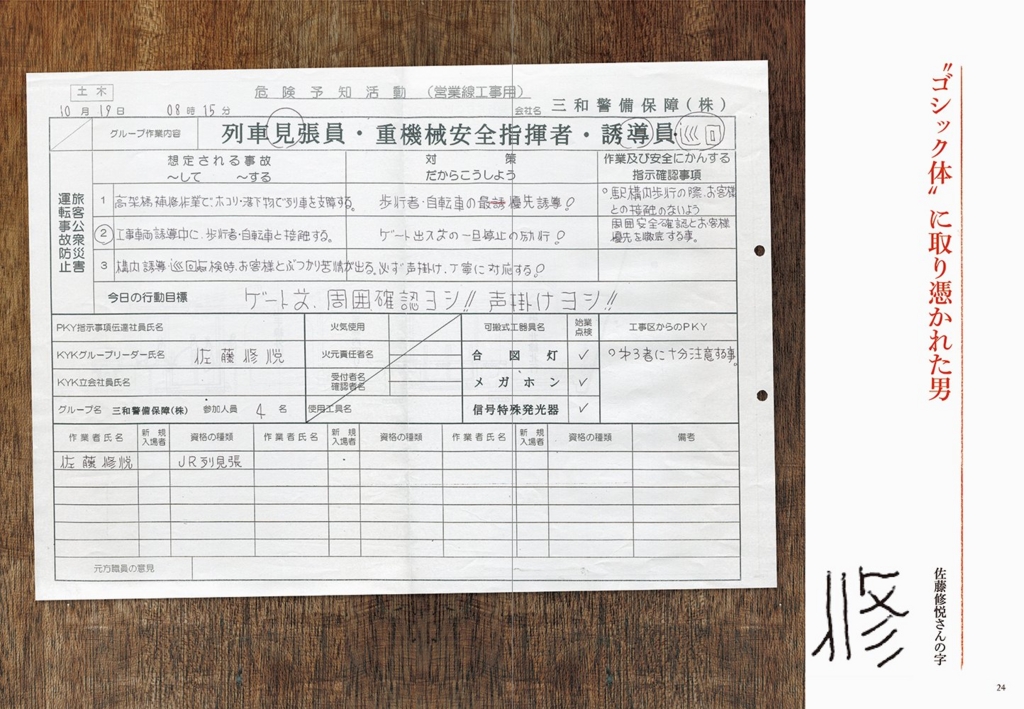
井原奈津子氏
くせ字愛好家。多摩美術大学卒業後、主にエディトリアルデザインに関わる。現在は筆耕、習字の指導などを行い、「くせ字練習会」などのワークショップも開催している。
マツコの知らない世界で取り上げられた「くせ字の世界」
2017年10月17日の「マツコの知らない世界」には井原奈津子氏自身が出演し「くせ字の世界」として取り上げられた。
くせ字蒐集家の井原奈津子は2017年10月17日のマツコ・デラックスの冠番組であり、TBS系列で放送されているトークバラエティ番組「マツコの知らない世界」に出演し、「くせ字の世界」を紹介された。
番組内で中森明菜や小沢健二などの書くくせ字が好みと語っていた。ただのファンにも思えてもくる内容でマツコにもあまりハマっていなかったようだが…。
私の愛するお気に入りのくせ字たちでは、くせ字を愛するきっかけとなった予備校講師の字、ガムテープを使用した案内表示文字の書体「修悦体」で知られる佐藤修悦さん、ミュージシャンの小沢健二などの文字を紹介。
修悦体
主にガムテープとカッターナイフを使用した直線とアールによって描かれた文字。2008年の映画『まぼろしの邪馬台国』の題字にも使用されている。
井原奈津子氏は番組中、小沢健二の文字は軽やかでポップで知的さもあって音楽そのものと絶賛。 マツコには伝わっていなかったようだが…。
その他にもまるもじを使いこなす松田聖子のくせ字や工業デザイナーの顔も持つ稲川淳二はレタリングに近く、読みやすさに乗っ取った製図で書くような見やすさが特徴の文字を書いている。また浜崎あゆみや中森明菜のくせ字を紹介した。